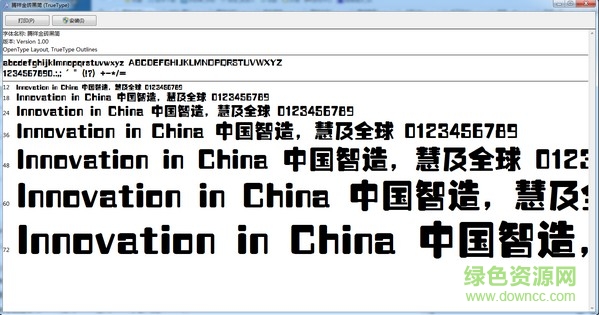
騰祥金磚黑簡(jiǎn)是北京騰祥科技研發(fā)的一款美術(shù)體字體,由于該字體的筆畫是以金磚的造型設(shè)計(jì)了,所以被稱為金磚字體,主要適用于印刷出版、兒童讀物、廣告設(shè)計(jì)等,有需要的快來(lái)下載使用吧。
此款字為美術(shù)體。由作者李大康提供設(shè)計(jì)創(chuàng)意初稿,騰祥設(shè)計(jì)團(tuán)隊(duì)二次設(shè)計(jì)制作完成。風(fēng)格鮮明、特點(diǎn)突出。筆畫是以金磚的造型為設(shè)計(jì)依據(jù),因此命 名為“金磚黑體”。全部筆畫均以方筆展現(xiàn)但與傳統(tǒng)黑體不同的是拐角處、轉(zhuǎn)折處 全部用倒角處理形成方中帶圓的效果,體現(xiàn)出字的圓潤(rùn)與厚重感。筆畫間搭配粗細(xì) 懸殊,字的造型重上輕下,厚左薄右,形成字面上的黑白反差,比較“耀眼”。用于大、小標(biāo)題字,寓意吉祥。本作品可適用于印刷出版兒童讀物、包裝設(shè)計(jì)、廣告 設(shè)計(jì)、網(wǎng)頁(yè)設(shè)計(jì)等。